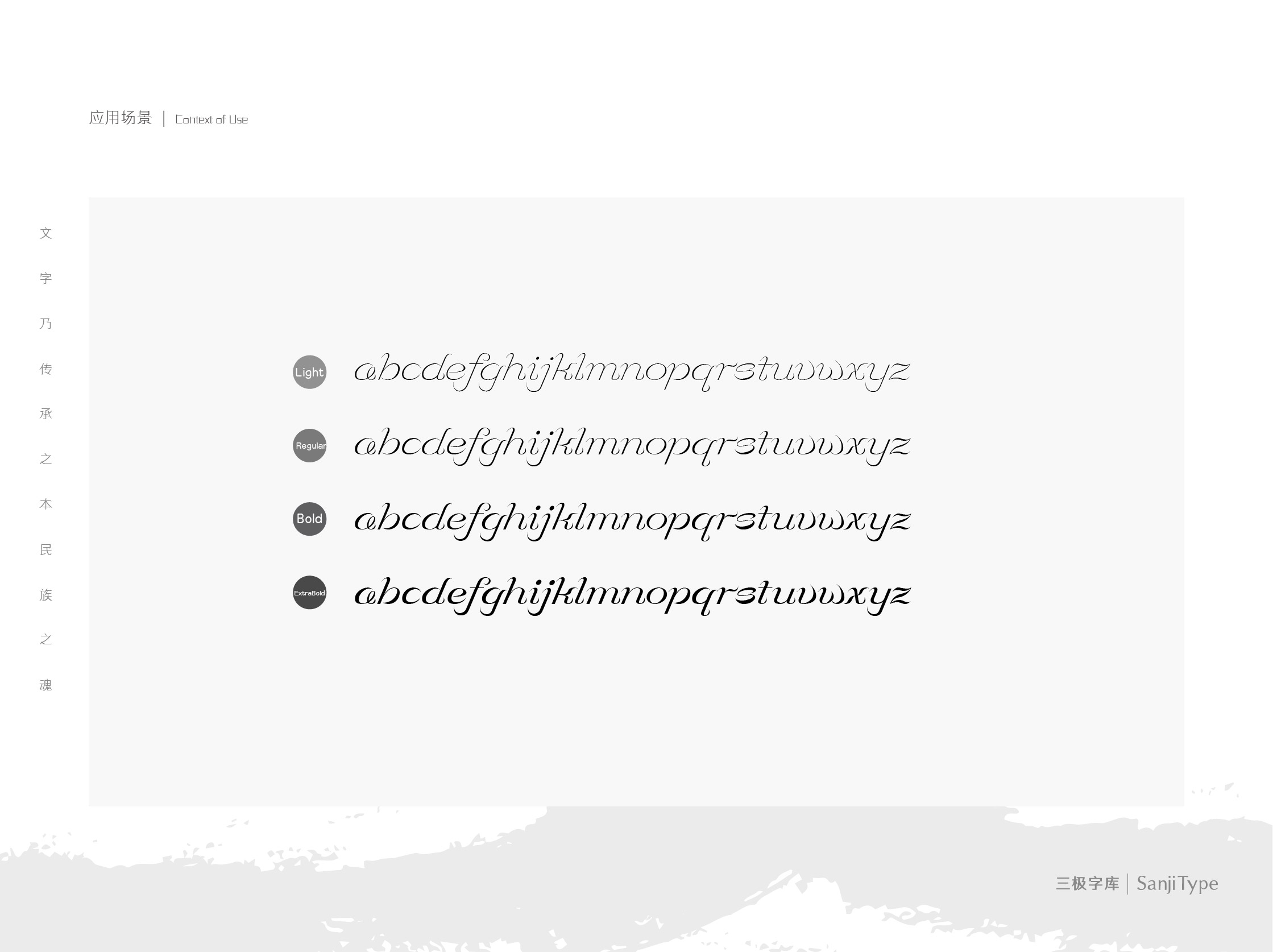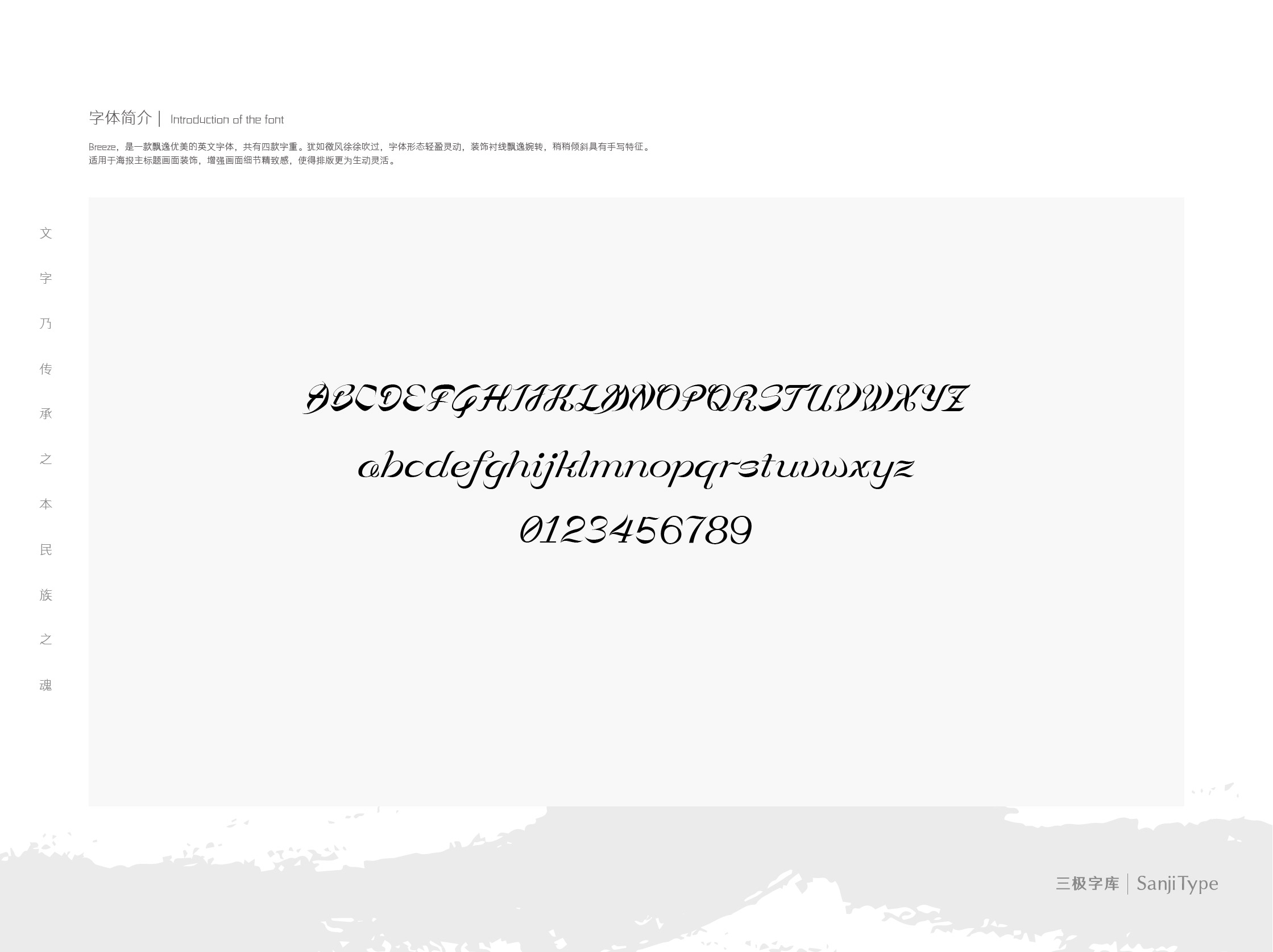
Breeze家族
Breeze-Light
Breeze-Regular
Breeze-ExtraBold
Breeze-Bold
Breeze,是一款飘逸优美的英文字体,共有四款字重。犹如微风徐徐吹过,字体形态轻盈灵动,装饰衬线飘逸婉转,稍稍倾斜具有手写特征。适用于海报主标题画面装饰,增强画面细节精致感,使得排版更为生动灵活。